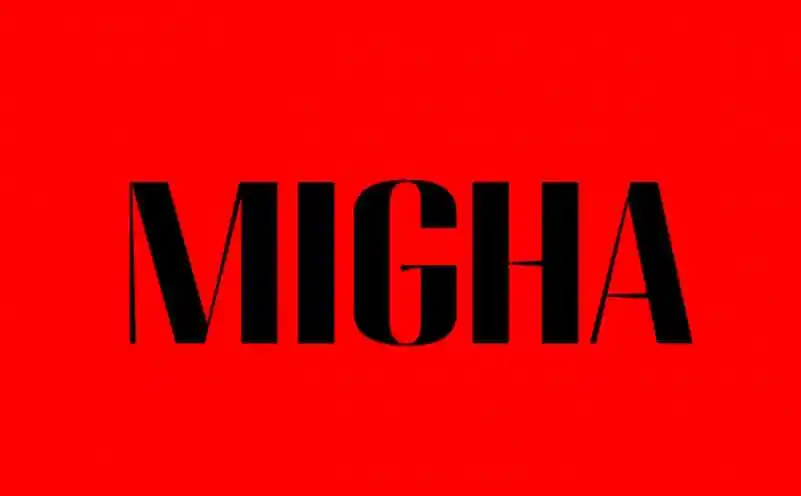
A Migha Sans Serif é uma elegante fonte geométrica que destaca-se por sua sofisticação arquitetônica. Ideal para projetos focados em temas como beleza e saúde, ela foi projetada pelo Seniors Studio e disponibilizada gratuitamente pela 99designs. Esta família de fontes apresenta seis pesos diferentes, quatro larguras, uma contraste e um desvio angular, totalizando 96 arquivos de fonte. O conjunto inclui a versão em maiúsculas completa, números, pontuação e suporte multilíngue. Perfeita para qualquer tipo de projeto gráfico, seja uma marca, revista, cartaz, logotipo ou postagem do blog, a Migha Sans Serif oferece um aspecto moderno com elementos vintage. Suas linhas curvas perfeitamente suaves e seus traços retos dão ao texto um apelo singular que certamente ressaltará sua apresentação. Seja você um designer gráfico atento às últimas tendências ou apenas aquele buscando uma fonte que complementa os temas de beleza e saúde, a Migha Sans Serif é uma ótima escolha para se juntar à sua coleção de recursos.